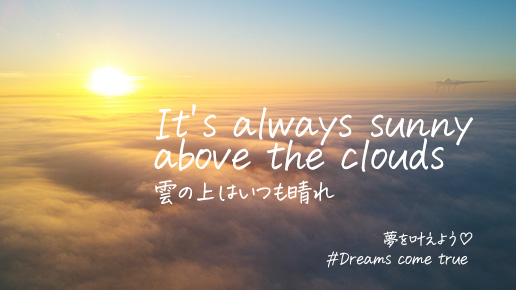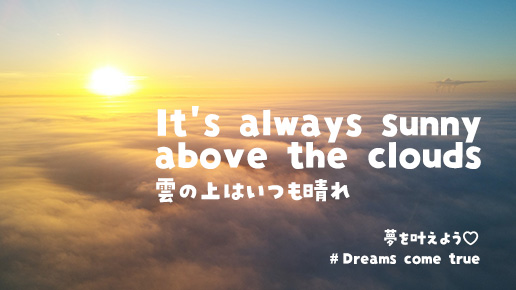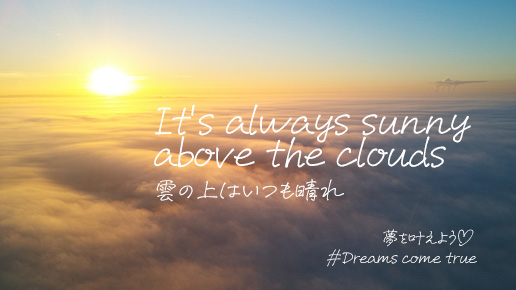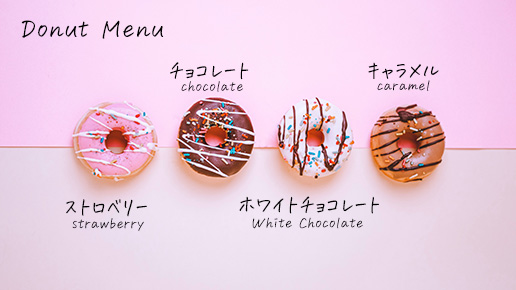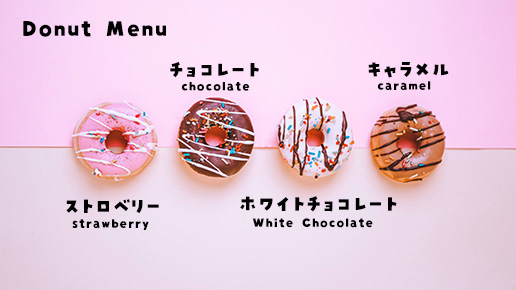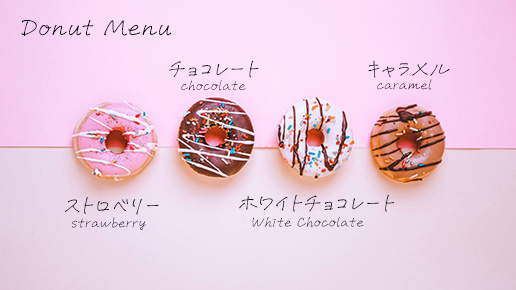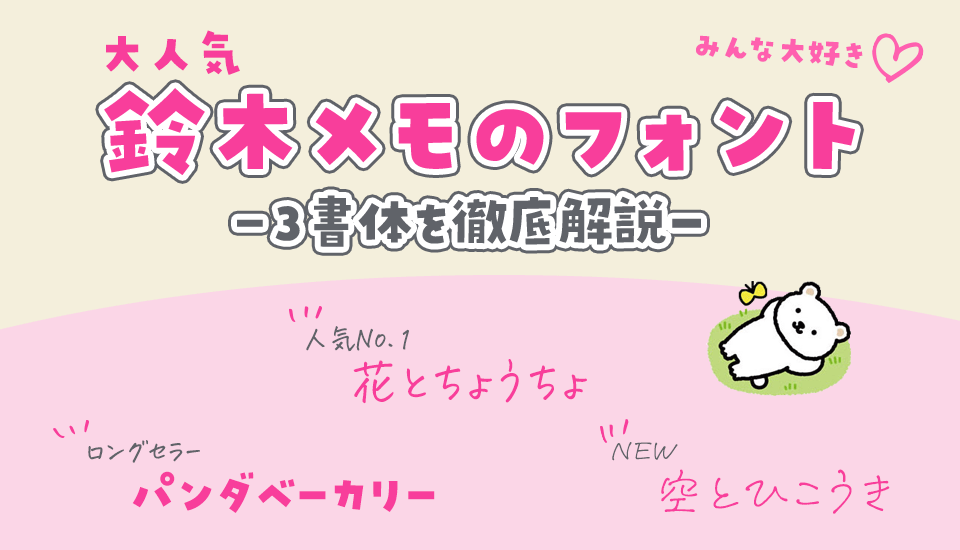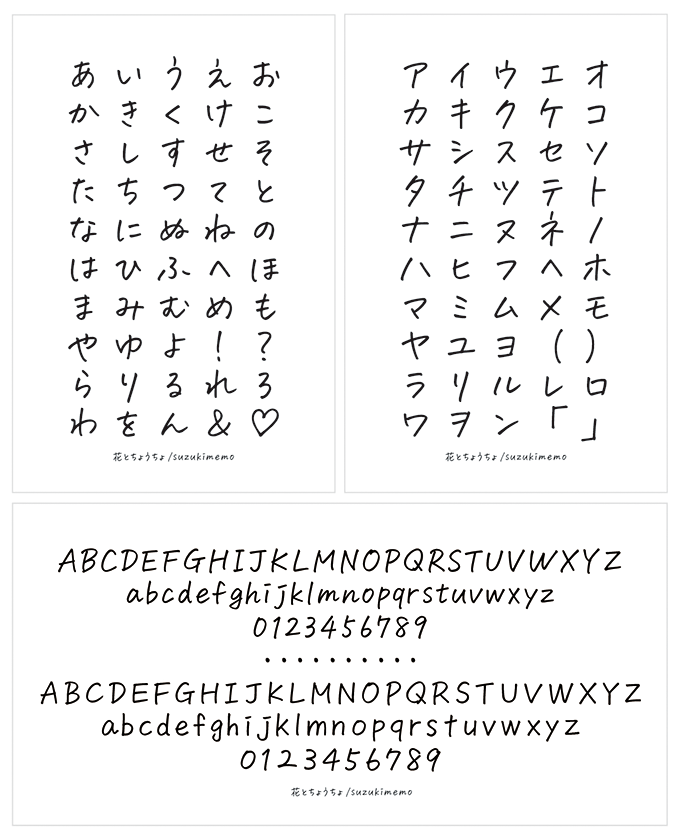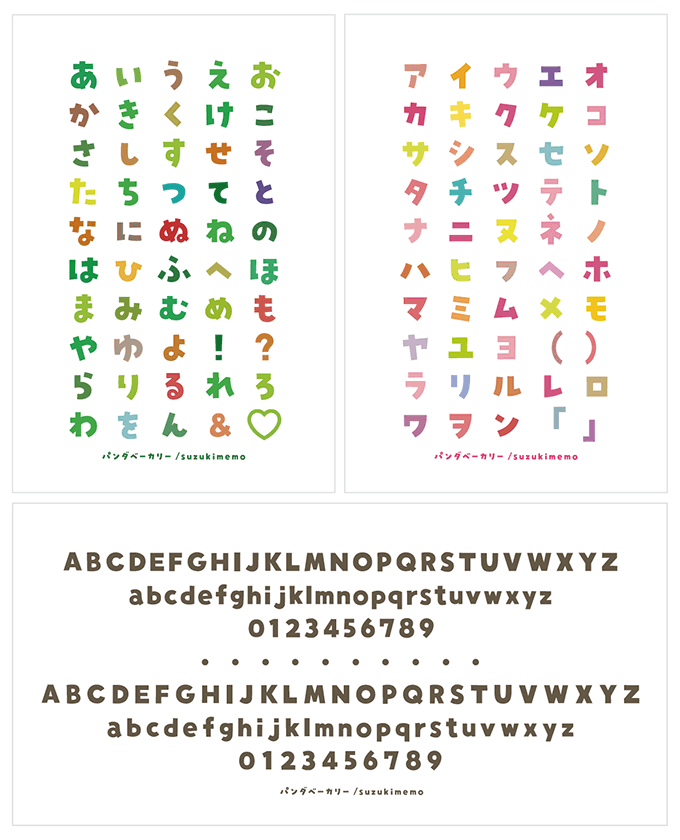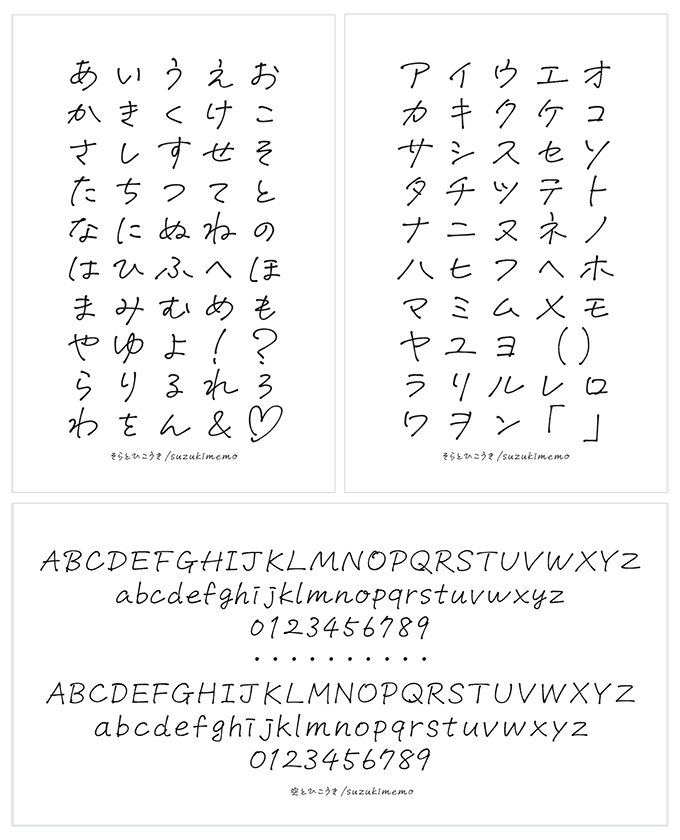
大人気 鈴木メモのフォント4書体徹底比較
今、大人気のフォントブランド「鈴木メモ」の4書体を徹底解説
インスタやXなどのSNSで話題となっている大人気のフォントブランド「鈴木メモ」。
「パンダベーカリー」「花とちょうちょ」「空とひこうき」「波とかもめ」は、”手書き感”の中にもそれぞれの個性をもったフォントです。印刷物、商品パッケージ、POP、テロップ、YouTube、Instagramなど、様々なシーンで使われているのを日々見かけるほど、ただ今人気沸騰中。
ここでは、各フォントの特徴の比較、4書体組み合わせたデザイン例をご紹介します。「鈴木メモ」フォントの世界観をご覧ください。
今回比較をした鈴木メモの手書きフォント
特徴を比較しました
パンダベーカリー
手描きのような自然なリズム感と、見出しやパッケージにも最適なしっかりとした太さのフォント
パンダベーカリー 手描きのような自然なリズム感
花とちょうちょ
ペンで書いたような右上がりの勢いがある、可愛らしいリアル系手書きフォント
花とちょうちょ ペンで書いたような右上がりの勢い
空とひこうき
手書きの勢い、万年筆のようなにじみやインク溜まりを活かした、さらりと書いたようなはしり書きフォント
空とひこうき さらりと書いたようなはしり書き
波とかもめ
丸いカーブと太めの線で柔らかい印象を与え、手書き文字の自然なリズム感が生まれるフォント
波とかもめ 丸みのある太めのフォント
字形で比較しました
パンダベーカリー
花とちょうちょ
空とひこうき
波とかもめ
同じデザインで比較しました
ポップで可愛い系のデザイン
パンダベーカリー
カラフルなPOP系デザインにピッタリ。しっかりとした太さもあり視認性も良好です。
花とちょうちょ
きれいな手書き風文字がおしゃれ感で女子力up! 大人っぽい印象になります。
空とひこうき
さらりと書いたはしり書きが、手作り感あるデザインを演出します。
波とかもめ
太めのデザインで視認性が高く、字形の丸っこさが親しみやすさを与えます。
エモい系のデザイン
パンダベーカリー
メッセージ性のあるデザインでも、しっかりと主張を伝えてくれます。
花とちょうちょ
きれいな手書き風文字は、デザイン性もメッセージ性も兼ね備えた、使い勝手の良い万能なフォントです。
空とひこうき
万年筆で書いたようなラフなフォントは手書き感が強く、よりメッセージが伝わります。
波とかもめ
太いマーカーで書かれたリラックスした雰囲気の手書きの文字は、感情をより直接的に伝え、親近感を深める効果があります。
4書体を組み合わせてみました
テイストの違う3書体ですが、鈴木メモブランドの特徴でもある「手書き感」で統一されたデザインは相性も良好。スッキリした中にもかわいらしさを感じさせます。